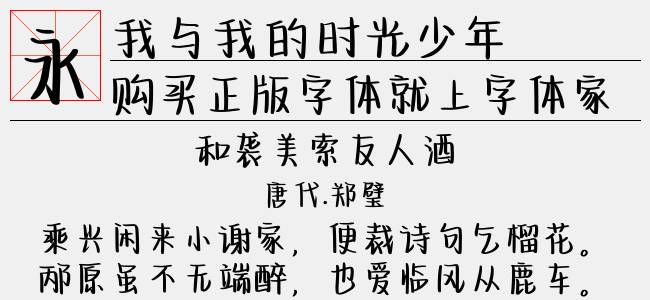
我与我的时光少年
字体作者:文道字库
字体名称:我与我的时光少年
字体家族:文道字库
字体公司:文道字库
我与我的时光少年
我与我的时光少年是文道字库推出的一款非常不错的艺术字体,风格比一般的字体更有特色,连贯字迹显得干练而不凌乱,清新简明,具有很好的视觉感,适合应用于艺术设计、平面宣传设计、网页设计,书法字帖等领域,欢迎喜欢我与我的时光少年字体的朋友前来下载使用。